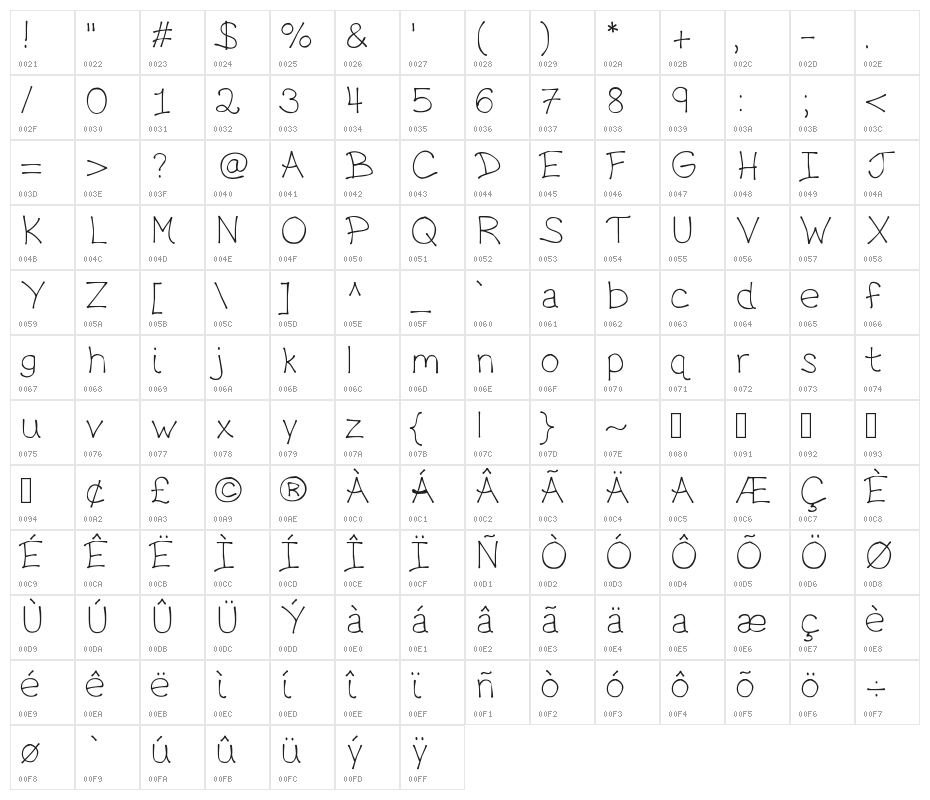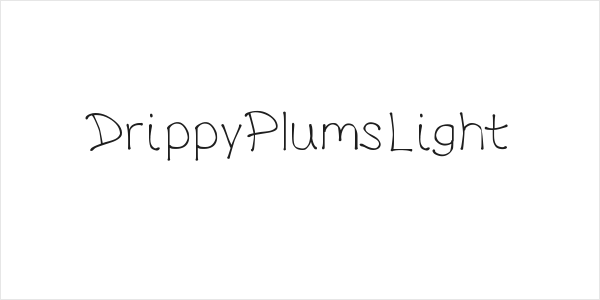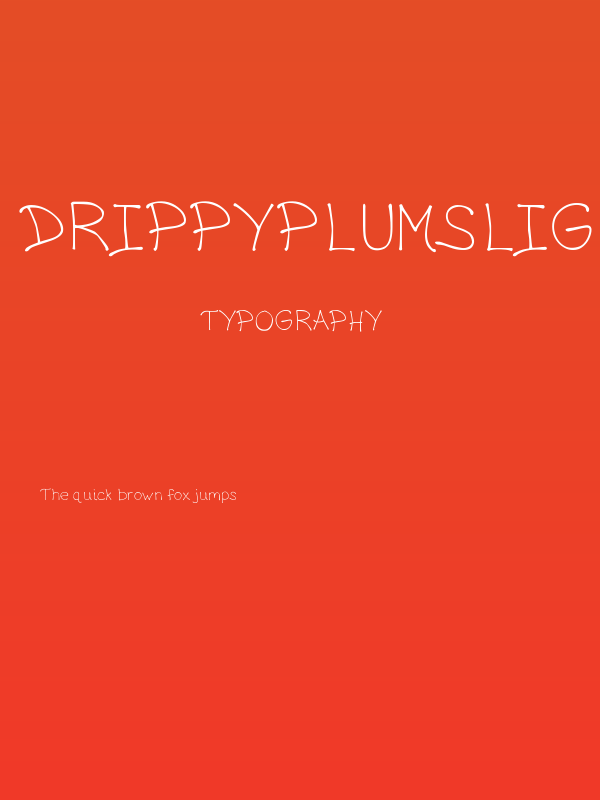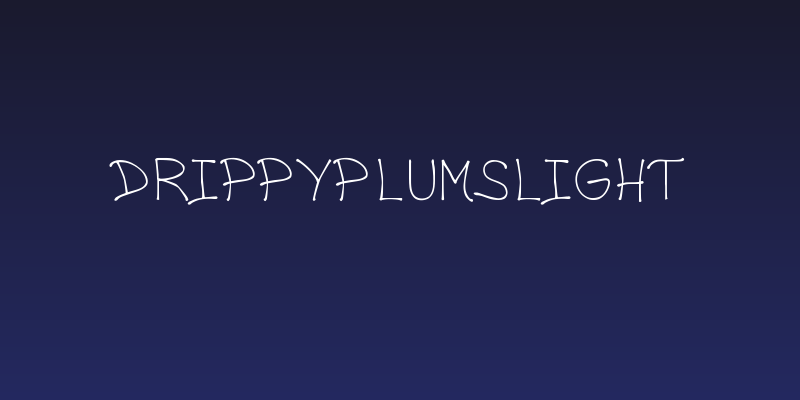
DrippyPlumsLight Font
| Gesamtstil | Casual, Playful |
| Anwendungsfall | Headlines, Informal text, Creative projects |
| Vorgeschlagene Projekte | Ideal for children's books, greeting cards, personal blogs, and playful branding. |